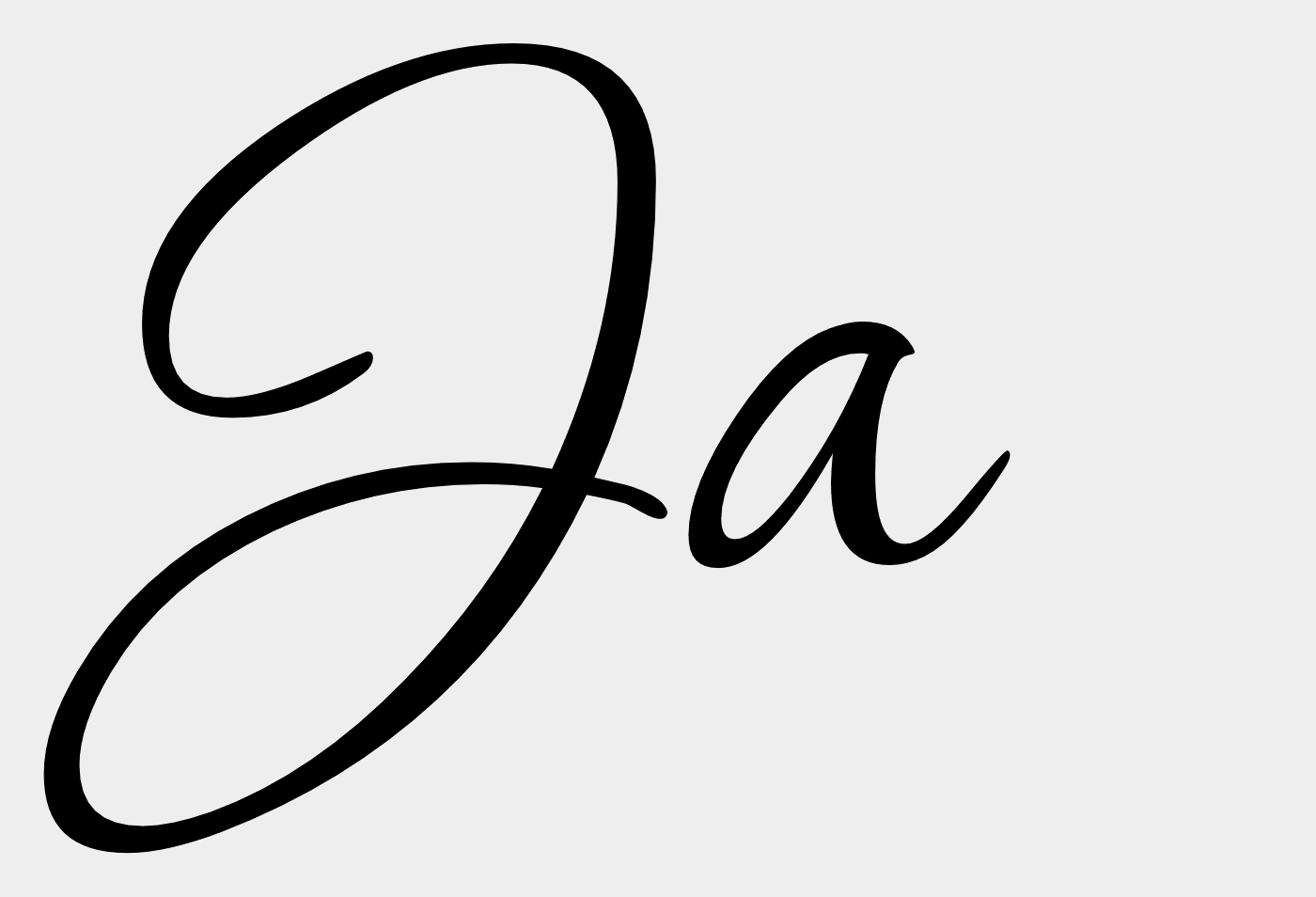
Auf der Suche ...
Ich suche händeringend für meine Tochter zur Hochzeit eine Schrift...
Ich habe nun meine Ordner mit meinen Schriften und das WWW durchwühlt, aber leider kann ich die Schrift vom "J" nicht finden.
Kann mir einer weiterhelfen und mir Schriften nennen, die so oder ähnlich aussehen. Wobei mir wichtig ist, das der Bogen am "J" oben geöffnet ist.